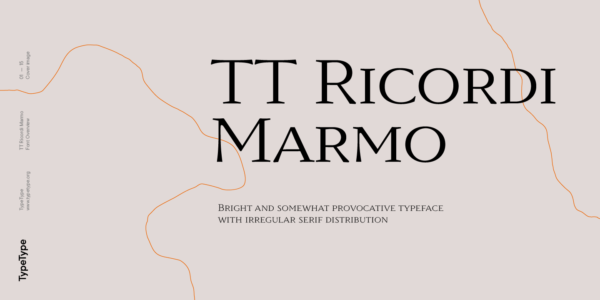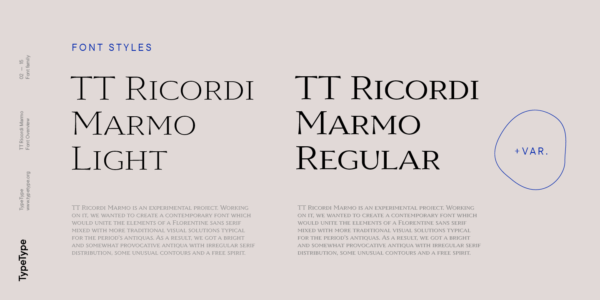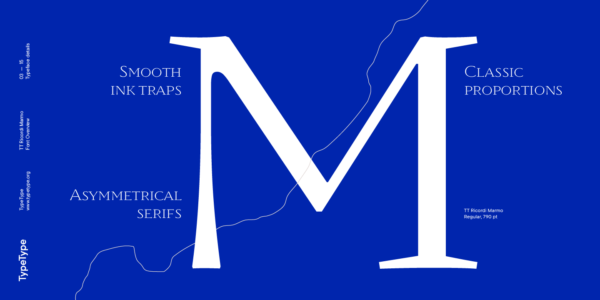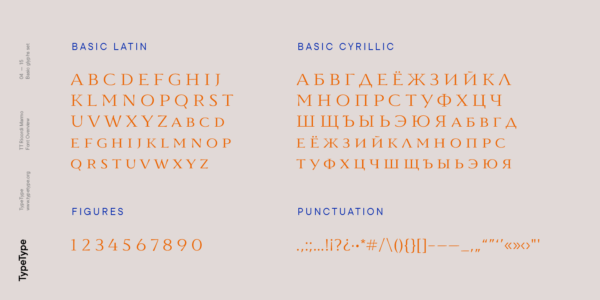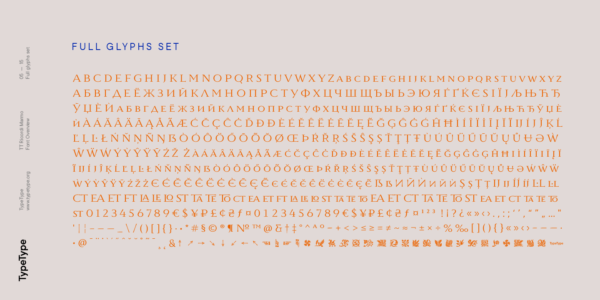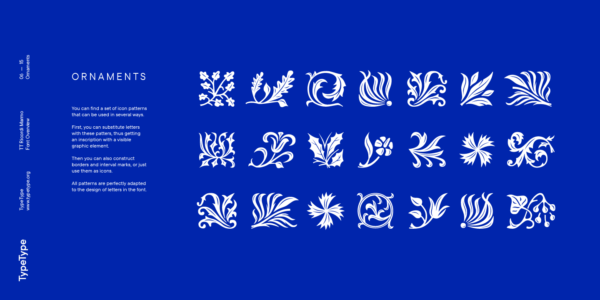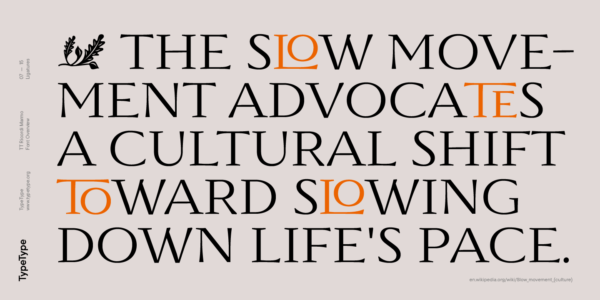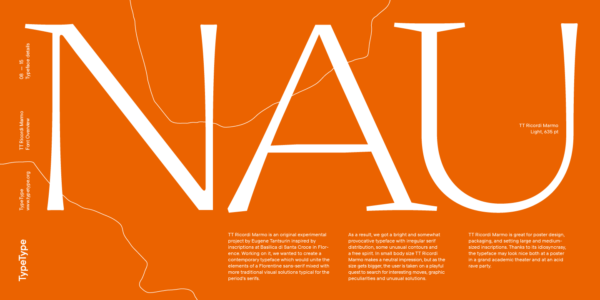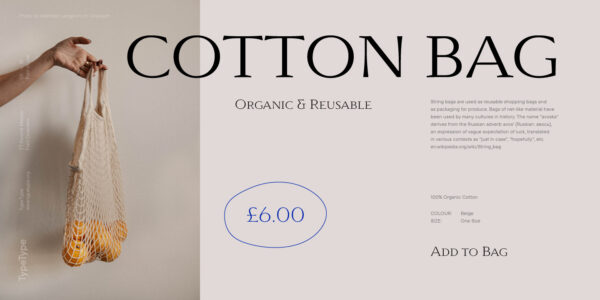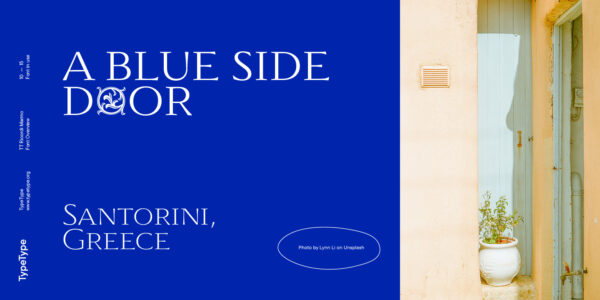
TT Ricordi Marmo
TT Ricordi Marmo — ТТ Рикорди Мармо
Произносится «ТТ Рикорди Мармо». «Ricordi» — производное слово от ricordo, с итальянского — «воспоминание», «Marmo» — в переводе с итальянского «мрамор». Буквы «TT» являются аббревиатурой названия компании.
TT Ricordi Marmo — яркая антиква с нерегулярным распределением засечек, необычными контурами и вольным характером. Шрифт вдохновлён старинными надписями.
TT Ricordi Marmo
Яркая и провокационная антиква с нерегулярным распределением засечек
TT Ricordi Marmo — авторский экспериментальный проект Евгения Танцурина, черпающий вдохновение в надписях из Basilica di Santa Croce, Florence. При работе над проектом мы хотели создать современный шрифт, который бы объединял в себе элементы Флорентийского гротеска, смешанные с более традиционными визуальными решениями свойственными для антикв того времени.
О гарнитуре TT Ricordi Marmo
TT Ricordi Marmo продолжает серию экспериментальных гарнитур, созданных в рамках проекта TT Ricordi. Основная идея этой уникальной серии — поиск «шрифтовых жемчужин» в старинных надписях на табличках и камнях и возвращение самых интересных из них к жизни в виде современных шрифтов.
TT Ricordi Marmo — авторский проект дизайнера Евгения Танцурина, вдохновленный надписями в базилике Санта-Кроче во Флоренции (Basilica di Santa Croce, Florence). Мы стремились создать современный шрифт, в котором элементы флорентийского гротеска смешались с более традиционными визуальными решениями, свойственными для антикв того времени. В результате получилась яркая и даже немного провокационная антиква с нерегулярным распределением засечек, необычными контурами и вольным характером.
В маленьком кегле TT Ricordi Marmo производит достаточно нейтральное впечатление. Однако в крупном размере он раскрывается с другой стороны: становятся заметны интересные ходы, графические особенности и нестандартные решения. Этот шрифт отлично подойдет для набора надписей крупного и среднего размера. Его можно использовать в дизайне плакатов, оформлении упаковок и обложек журналов. При этом за счет своей необычности TT Ricordi Marmo будет одинаково хорошо смотреться в разных проектах — как в строгих и элегантных, так и в современных и дерзких.
В гарнитуру входит сет орнаментов-иконок. Ими можно заменять некоторые буквы, чтобы получилась надпись с яркими графическими элементами. Также из них можно собирать бордюры и отбивки или просто использовать их в виде иконок. Все орнаменты отлично адаптированы к буквам в шрифте.
TT Ricordi Marmo создавался как плакатный шрифт, поэтому строчной набор в нем заменяет капитель. Кроме того, в шрифте есть сет дискретных лигатур, которые тоже способствуют разнообразию набора, а еще — стилистические альтернативы, стрелочки и ручки.
Состав TT Ricordi Marmo:
• 2 начертания и 1 вариативный шрифт;
• 630 глифов в каждом начертании;
• 18 OpenType фич;
• поддержка более 190 языков.
ss01 | Alternative latin E
Ee
ss02 | Alternative Eszett
ß
ss03 | Alternative Cyrillic I
Ии
ss04 | Alternative Ampersand
&
dlig | Discretionary Ligatures
CT LA
case | Case Sensitive Forms
({[H]})